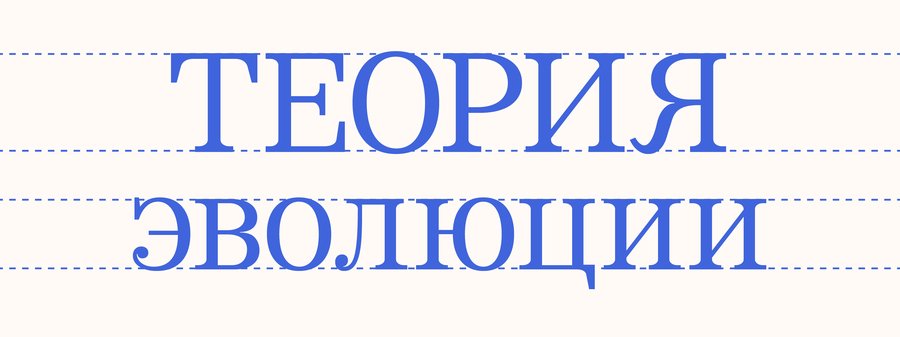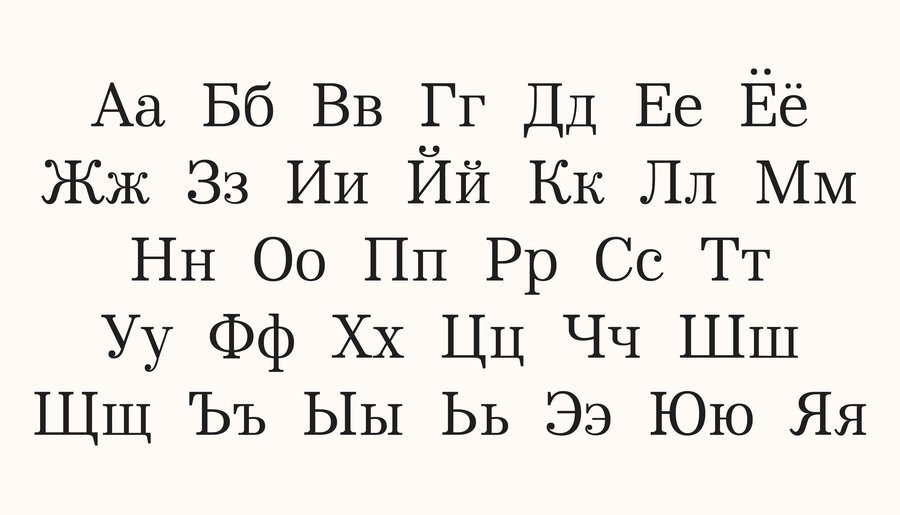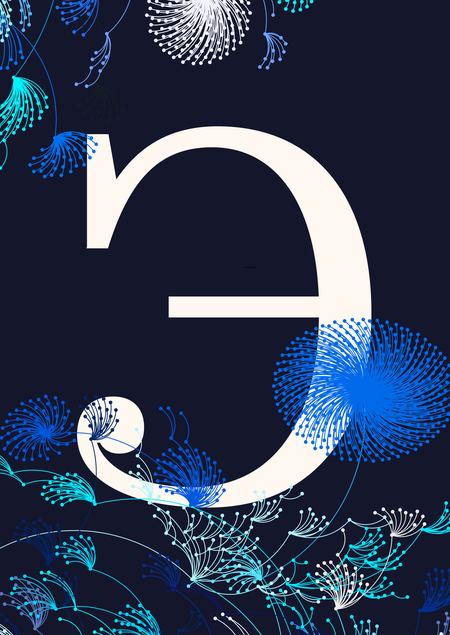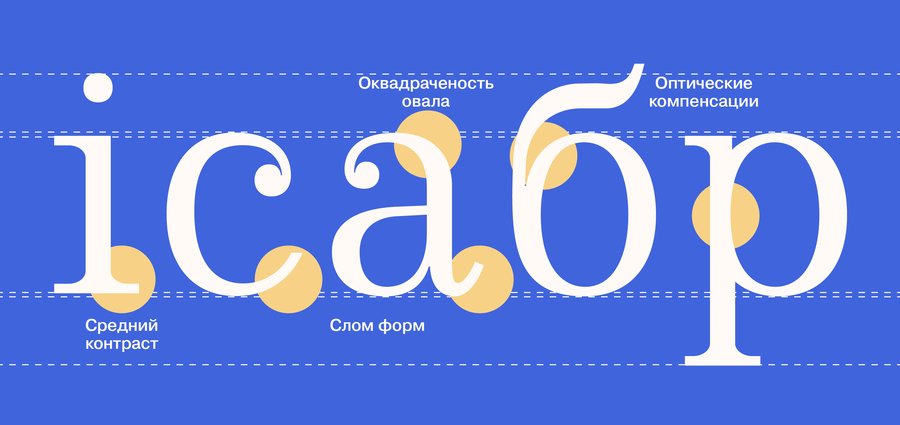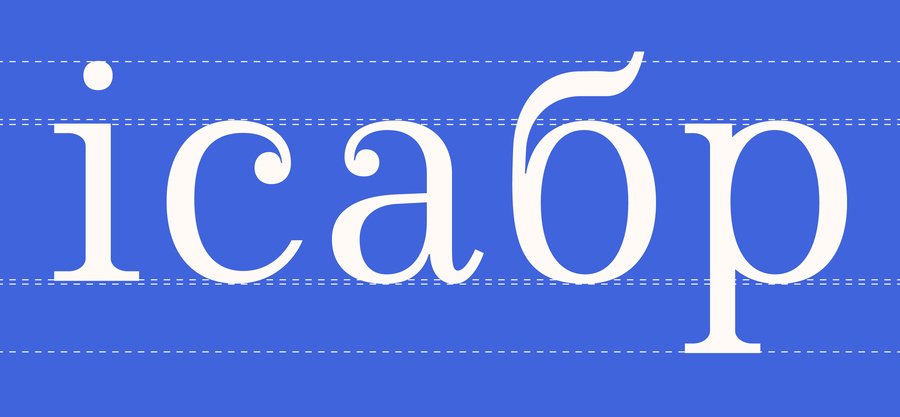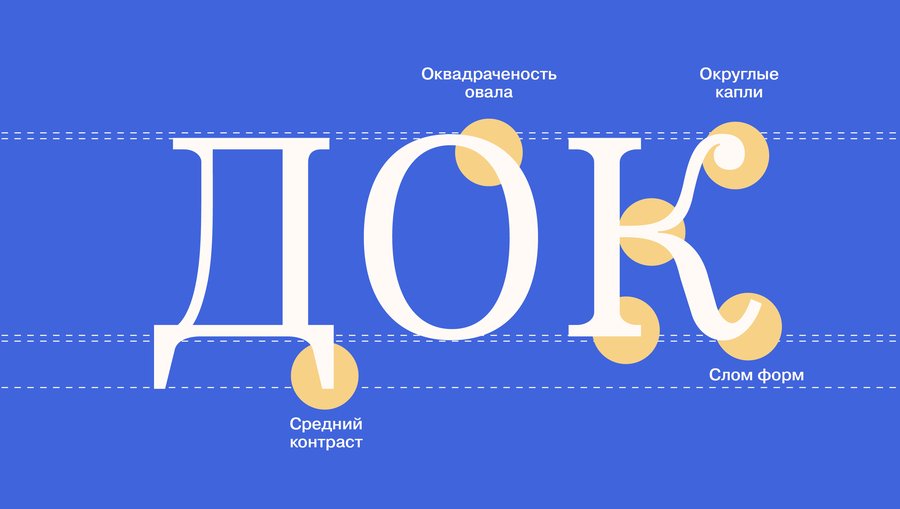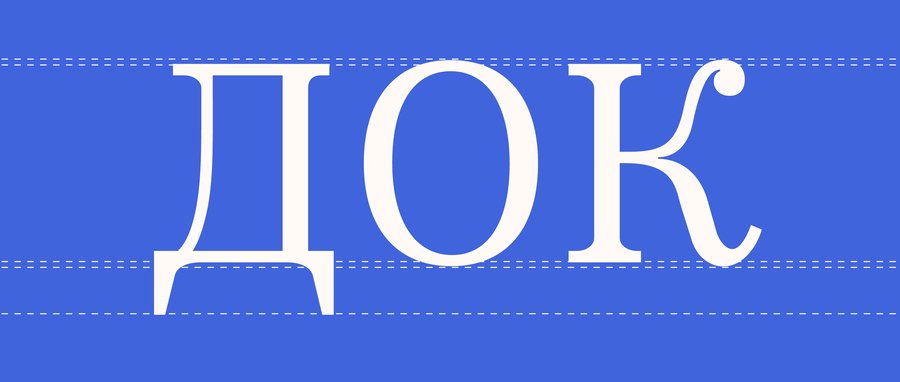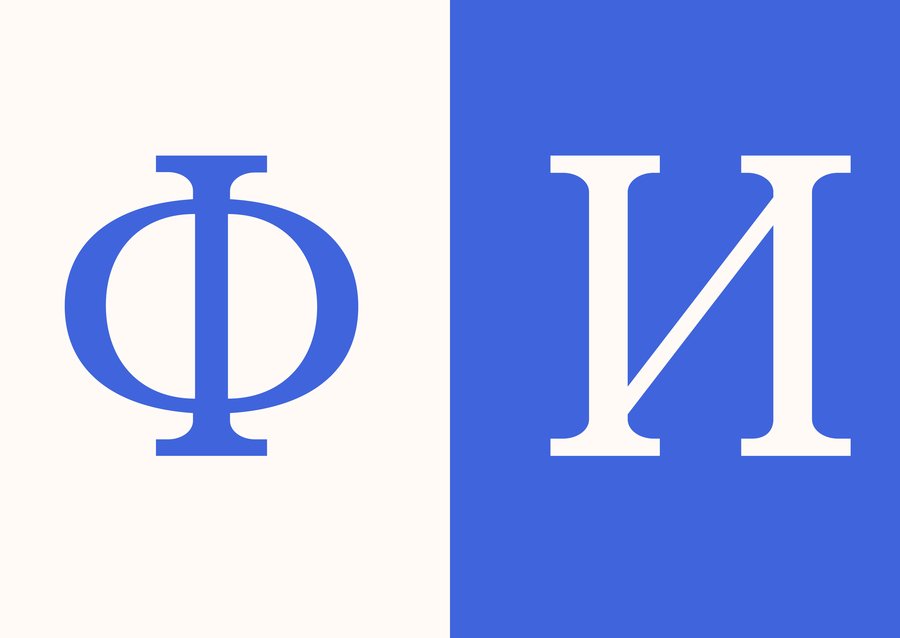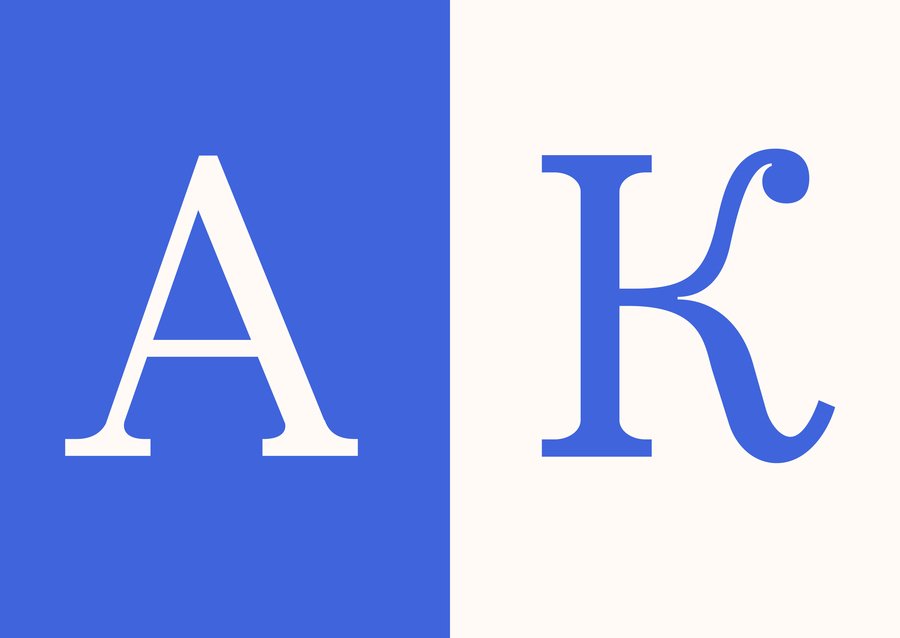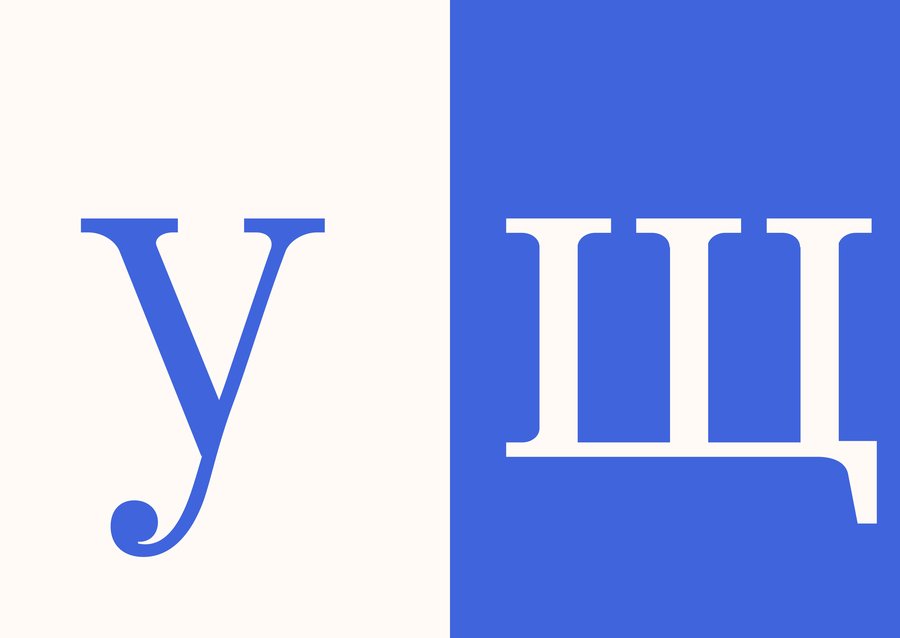
Evolutio — шрифт, вдохновлённый типографикой Clarendon и визуальной культурой научной эпохи второй половины XIX века.
Шрифт переосмысляет историческую музейную графику через систему строгих форм, устойчивых вертикалей и современных деталей. Evolutio передаёт атмосферу научного исследования, каталогизации и эволюционных открытий, где типографика становится частью смыслового пространства.
Строение
Кириллица
Размеры (display)
Латиница
Цифры и пунктуация
Знаковый состав — 155 глифов
Примеры использования в брендинге Дарвиновского Музея